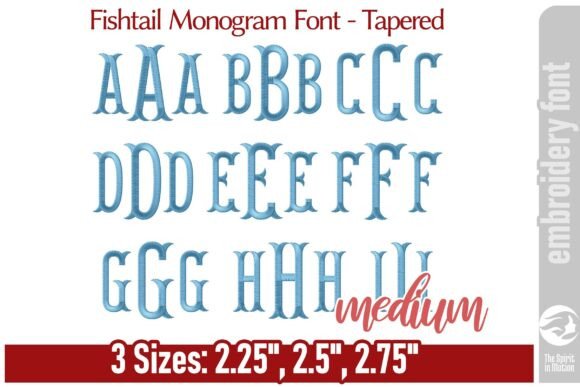
Fishtail Monogram Font - Tapered / M
Пошук відповідних елементів дизайну може бути складним, але Fishtail Monogram Font - Tapered / M пропонує виняткову колекцію, яка миттєво покращить вашу роботу.